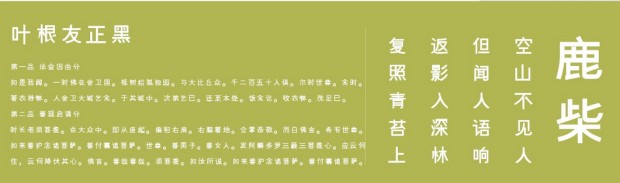
軟件介紹 軟件標(biāo)簽: 葉根友字體 字體 葉根友正黑字體是葉根友字體中最新推出的一款字體,字形非常漂亮,正直剛毅,有需要的就來綠色資源網(wǎng)下載吧!葉根友正黑字體預(yù)覽葉根友正黑字體安裝方式1、首先選中你下載的打包字體,并解壓你下載的字體壓縮包。2、Win Vista\Win 7\Win 8系統(tǒng):鼠標(biāo)右鍵單擊字體文件,然后點(diǎn)擊 > "Install" 安裝字體 3、Windows XP(2000\98)系統(tǒng):把解壓好的字體文件放入 C:\Windows\Fonts 目錄中即可 軟件截圖 上一張下一張(1 / 1) 安裝詳細(xì)截圖 猜你喜歡 葉根友 葉根友 葉根友字體是現(xiàn)代社會(huì)中使用最為廣泛的字體,包含葉根友疾風(fēng)草書、葉根友刀鋒黑草等,現(xiàn)綠色資源網(wǎng)小編整合幾款葉根友字體大全供用戶下載,歡迎到綠色資源網(wǎng)體驗(yàn)! 查看更多>> 葉根友哲在手寫字體 4.00M/中文/6.0/官方版下載 葉根友離賢行書字體 10.00M/中文/5.7/免費(fèi)版下載 南構(gòu)字體合集 50.00M/中文/3.7/共16款下載 南構(gòu)汪本友行書字體 10.00M/中文/3.3/下載 南構(gòu)標(biāo)羽歌士體 10.00M/中文/5.0/免費(fèi)版下載 南構(gòu)王天喜行書簡體字體 10.00M/中文/2.1/下載 其他版本下載 標(biāo)題 大小 更新日期 下載 下載地址 電腦版 葉根友正黑 點(diǎn)擊報(bào)錯(cuò) 軟件無法下載或下載后無法使用,請(qǐng)點(diǎn)擊報(bào)錯(cuò),謝謝! 關(guān)閉報(bào)錯(cuò)反饋 請(qǐng)描述您所遇到的錯(cuò)誤,我們將盡快予以修正,謝謝! *必填項(xiàng),請(qǐng)輸入內(nèi)容 本類最新 葉根友字體庫打包 共18款 葉根友風(fēng)帆特色簡體 免費(fèi)官方版 葉根友哲在手寫字體 官方版 南構(gòu)村花手寫體ttf版 南構(gòu)王小花手寫ttf常規(guī) 南構(gòu)日漫風(fēng)字體 相關(guān)文章 Photoshop字體安裝使用方法和技巧 如何解決“無法新增字體”問題 Win 7系統(tǒng)安裝字體方法 網(wǎng)頁字體大小設(shè)置方法 怎么改網(wǎng)頁字體大小 在Linux系統(tǒng)中安裝字體的幾種方法 windows7字體顯示問題:打開某些程序的時(shí)候顯示的是亂碼 用戶評(píng)論 熱門評(píng)論 最新評(píng)論 發(fā)表評(píng)論 查看所有評(píng)論(0) 昵稱: 請(qǐng)不要評(píng)論無意義或臟話,我們所有評(píng)論會(huì)有人工審核. 字?jǐn)?shù): 0/500 (您的評(píng)論需要經(jīng)過審核才能顯示)